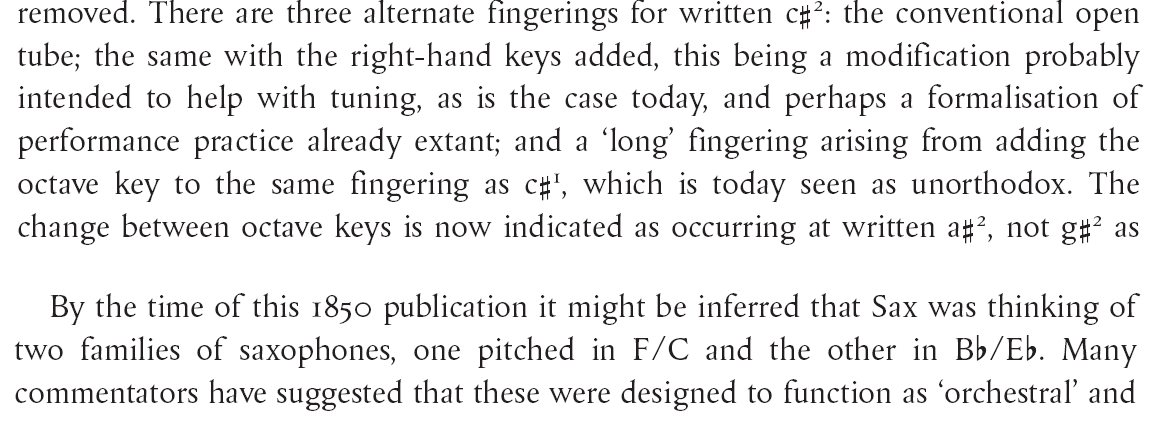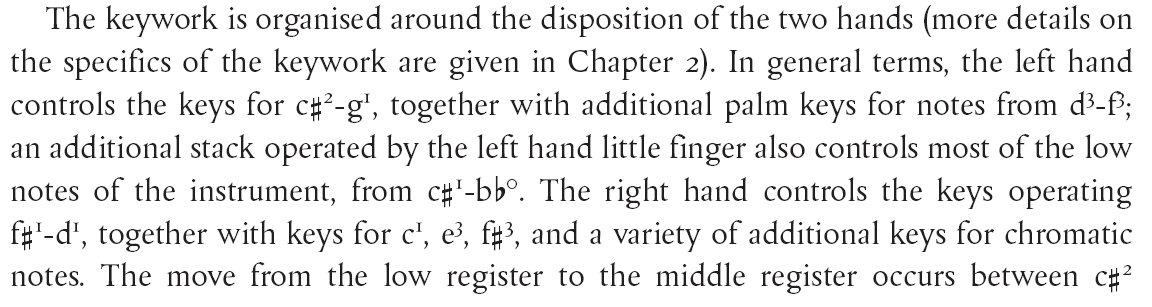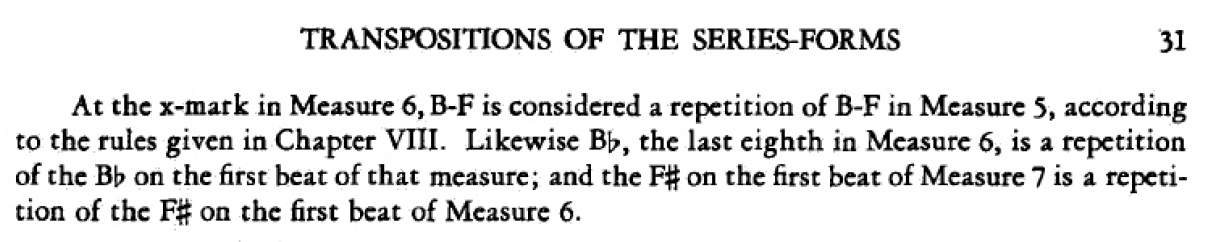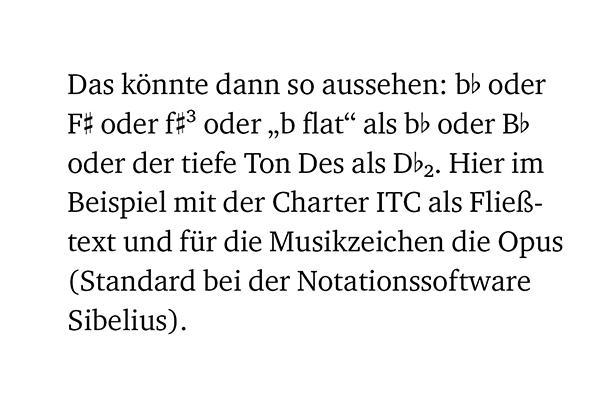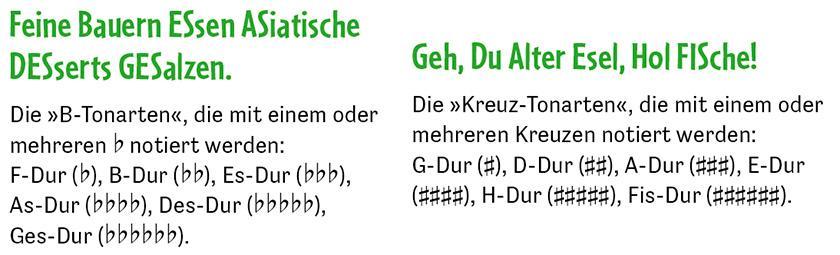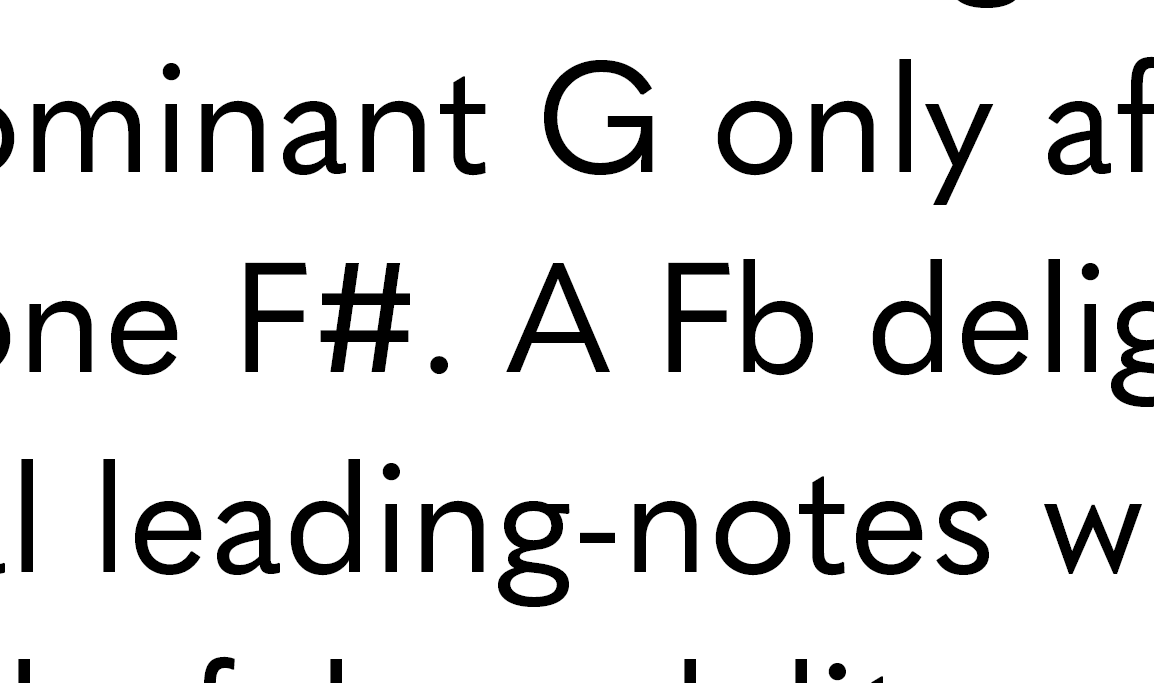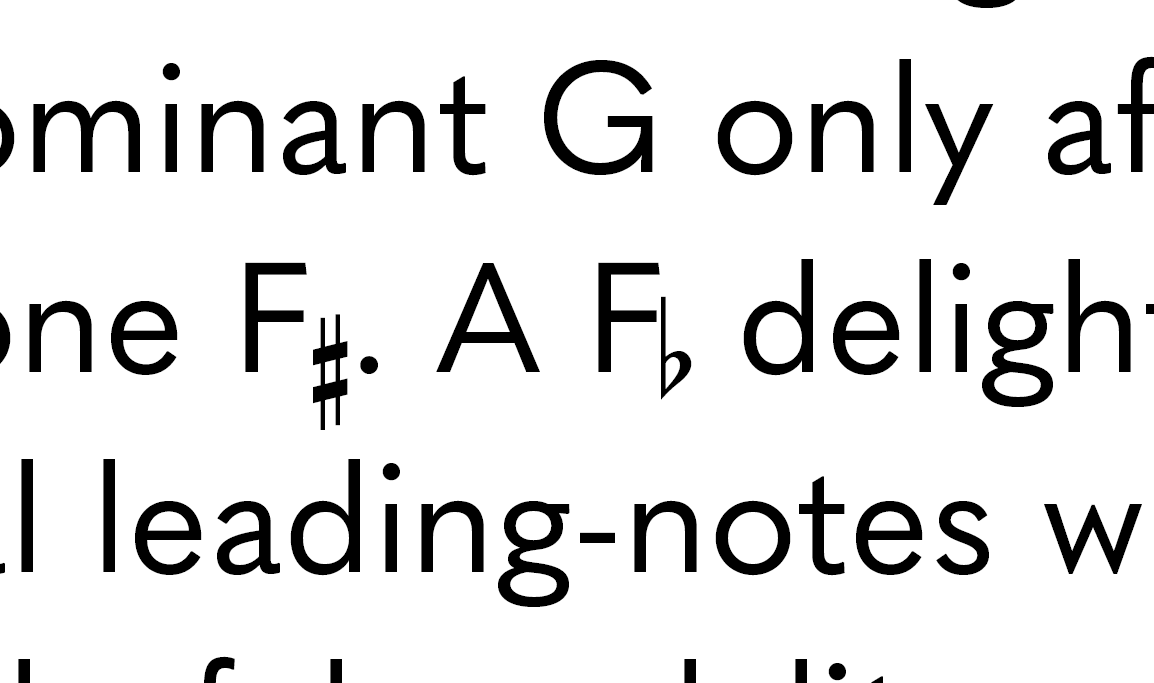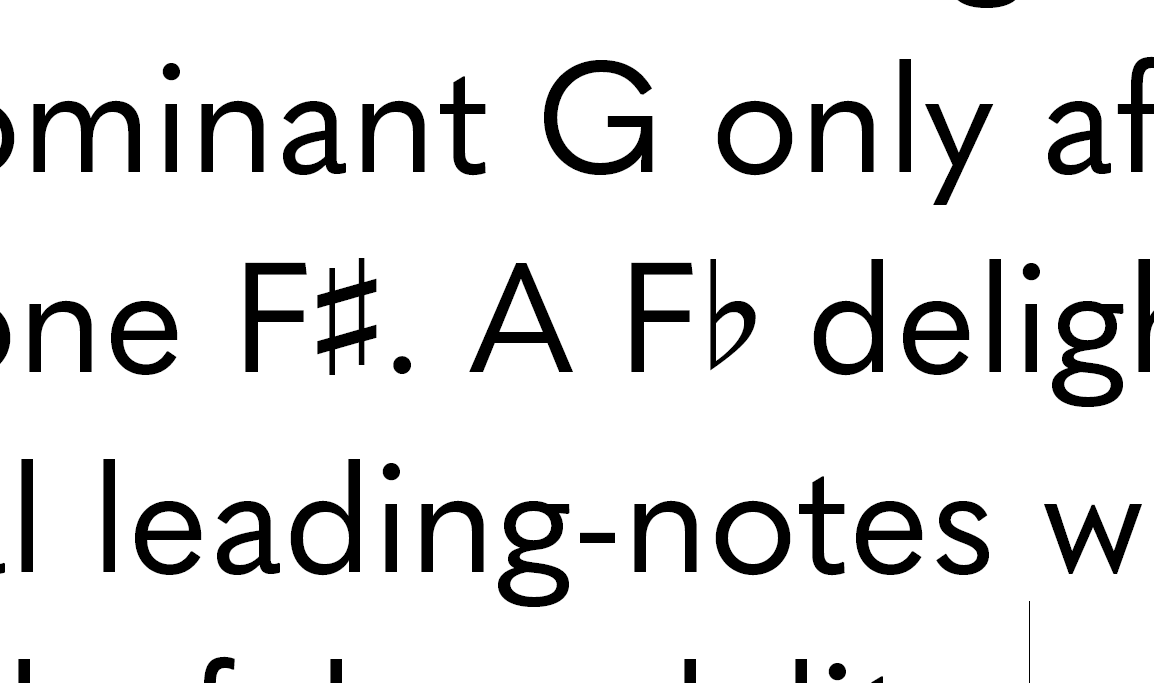
[Mitglied Loth…] Geschrieben 9. Januar Teilen Geschrieben 9. Januar Es ist im englischen Sprachraum durchaus üblich, erhöhte und erniedrigte Noten mit den aus der Notenschrift bekannten Zeichen ♯ und ♭ zu schreiben. Zum Beispiel wird die Note Fis zu F♯, Fes wird zu F♭. Aus der Detailtypografie von De Jong/Forssman weiß ich inzwischen, dass die Verwendung der Raute (#) hier nicht richtig ist. Das kleine »b« in der Brotschrift ist hier nicht deutlich. Das Manuskript sieht aber manchmal so aus: [[Abb. 1]] Tatsächlich enthält unsere Hausschrift die besagten Glyphen gar nicht. Das ♯ konnte ich im Unicode auf Position U+266F (Musical Sharp Sign) und das ♭ auf Position U+266D (Musical Flat Sign) ausfindig machen. Ich bin aber erstaunt, dass nur wenige Fonts die Zeichen beinhalten. Recht klar ist, dass die Sonata Regular von Adobe dabei ist. Das sieht dann so aus: [[Abb. 2]] Das sind richtige Fremdkörper und die Zurichtung ist ja wohl auch nicht für Text gemacht. Ich nehme an, die Sonata ist für den Notensatz gedacht. Nach etwas Recherche habe ich die Arial Unicode MS gefunden. [[Abb. 3]] Ich habe dann jeweils die Größe und den Grundlinienversatz angepasst und an der Mittellänge ausgerichtet. [[Abb. 4]] Link zu diesem Kommentar
[Mitglied Phoi…] Geschrieben 9. Januar Teilen Geschrieben 9. Januar Generell gesagt, sind falsch und richtig relative Größen, typographisch falsch genutztes kann durch die Akzeptanz und Gewohnheit der Zielgruppe zu "richtig" werden oder auch als "richtig" aufgefasst werden, so dass tatsächlich korrekte Anwendungen zu Stolpersteinen werden, die "falsch" wirken -- solange es keine wirklich gute Alternative gibt. Bei Abbildung vier würde ich das Erhöhungszeichen nicht an der Ecken des Querstrichs ausrichten, sondern am oberen Kreuzungspunkt. Ich bin nun kein Experte für irgendwas, aber ich erinnere mich aus dem Schulunterricht, dass die Modifikationen eigentlich vor der Note stehen müssen. Daher finde F# und Fb inkonsequent. #F und bF wären der Notation näher, F# und Fb der sprachlichen Verarbeitung. Ich würde mir da den Konflikt ersparen und einfach Fis und Fes schreiben. Link zu diesem Kommentar
[Mitglied D2C…] Geschrieben 9. Januar Teilen Geschrieben 9. Januar vor 16 Minuten schrieb Phoibos: Generell gesagt, sind falsch und richtig relative Größen, typographisch falsch genutztes kann durch die Akzeptanz und Gewohnheit der Zielgruppe zu "richtig" werden oder auch als "richtig" aufgefasst werden, so dass tatsächlich korrekte Anwendungen zu Stolpersteinen werden, die "falsch" wirken -- solange es keine wirklich gute Alternative gibt. Du meinst so etwas wie »25 x 25cm« statt »25 × 25 cm«? vor 17 Minuten schrieb Phoibos: Ich bin nun kein Experte für irgendwas, aber ich erinnere mich aus dem Schulunterricht, dass die Modifikationen eigentlich vor der Note stehen müssen. Daher finde F# und Fb inkonsequent. #F und bF wären der Notation näher, F# und Fb der sprachlichen Verarbeitung. Ich würde mir da den Konflikt ersparen und einfach Fis und Fes schreiben. Die Bilder legen nahe, dass es um englischen Text geht. »Fis« und »Fes« dürften auf Englisch nicht verstanden werden. 1 Link zu diesem Kommentar
[Mitglied Phoi…] Geschrieben 9. Januar Teilen Geschrieben 9. Januar vor 8 Minuten schrieb D2C: Du meinst so etwas wie »25 x 25cm« statt »25 × 25 cm«? Exakt. Oder drei Punkte statt Dreipunkt. Es gibt so vieles, was aus der Schreibmaschinenzeit sich so ins Zielgruppengedächtnis eingebrannt hat, dass die korrekte Anwendung erstmal zum Stolpern anregt. vor 13 Minuten schrieb D2C: »Fis« und »Fes« dürften auf Englisch nicht verstanden werden. Stimmt, Die Nutzung der Detailtypographie ließ mich an eine Übertragung denken. Die englische Wikipedia kennt übrigens mehrere Unicode-Punkte für das Kreuz: Zitat In Unicode, assigned sharp signs are as follows: U+266F ♯ MUSIC SHARP SIGN (HTML ♯ · ♯) U+1D12A 𝄪 MUSICAL SYMBOL DOUBLE SHARP (HTML 𝄪) U+1D130 𝄰 MUSICAL SYMBOL SHARP UP (HTML 𝄰) U+1D131 𝄱 MUSICAL SYMBOL SHARP DOWN (HTML 𝄱) U+1D132 𝄲 MUSICAL SYMBOL QUARTER TONE SHARP (HTML 𝄲) Link zu diesem Kommentar
[Mitglied Tobi…] Geschrieben 9. Januar Teilen Geschrieben 9. Januar Die gezeigten Beispiele sehen erstmal alle komisch aus. Das liegt evtl. aber auch daran, dass es um Fließtext geht und hier Ausschnitte gezeigt werden. Zum Richtigen Einschätzen, wäre eine ganze Seite mal interessant (zu lesen). Die Gewohnheit des Zielpublikums ist natürlich wichtig, denen kommen diese Zeichen vielleicht nicht so fremd vor wie mir Damit die Zeichen sich mehr einreihen, aber nicht falsch gelesen werden, würde ich mal versuchen # und b zu verwenden, aber das b in dem kursiven Schnitt. Das könnte eine gut lesbarer Kompromiss sein. Dagegen spricht natürlich, dass das ♭ein festes Zeichen ist, ähnlich wie Estimated ℮ oder €. Letzteres zeigt aber, dass konkrete Symbole auch ein Eigenleben bekommen können … Ansonsten finde ich Abb. 4 schon ganz gut. Das # würde ich etwas höher setzen und optisch auf x-Höhe mitteln statt rein rechnerisch nach Hilfslinien. Link zu diesem Kommentar
[Mitglied Henn…] Geschrieben 9. Januar Teilen Geschrieben 9. Januar Spontan hätte ich die Versetzungszeichen klein und hochgestellt gesetzt. Das liegt aber wahrscheinlich daran, dass so Akkordsymbole notiert werden, die ich wesentlich häufiger lese als englischsprachige Literatur. Ich habe mal zwei Beispiele aus Büchern angehängt: Ernst Krenek: Studies in Counterpoint, Schirmer, New York 1940: Stephen Cottrell: The Saxophone, Yale University Press, New Haven and London 2012: 2 Link zu diesem Kommentar
[Mitglied Uwe…] Geschrieben 9. Januar Teilen Geschrieben 9. Januar Hallo, ♯ vor 23 Minuten schrieb HenningH: Spontan hätte ich die Versetzungszeichen klein und hochgestellt gesetzt. Das liegt aber wahrscheinlich daran, dass so Akkordsymbole notiert werden, die ich wesentlich häufiger lese als englischsprachige Literatur. ...[...]... Stephen Cottrell: The Saxophone, Yale University Press, New Haven and London 2012: Der letzte Absatz ist inkonsequent? Bei B♭/E♭ ist das ♭ nicht runtergesetzt, das ♯ ist es jedoch. Oder wird da ein Unterschied zwischen Note und Tonart gemacht? Ich bin übrigens auch die hochgesetzten ♭ und ♯ von den Akkordsymbolen gewohnt. MfG Link zu diesem Kommentar
[Mitglied Thom…] Geschrieben 9. Januar Teilen Geschrieben 9. Januar Hier ein Beispiel aus der eigenen Mache. Die Musikzeichen sind aus der Textschrift (Kaius) und nicht aus einer speziellen Notenschrift gesetzt. Sie fügen sich daher gut ein, entbehren aber des für Notenzeichen typischen Strichkontrasts. 1 Link zu diesem Kommentar
[Mitglied Tobi…] Geschrieben 9. Januar Teilen Geschrieben 9. Januar vor 4 Minuten schrieb Thomas Kunz: entbehren aber des für Notenzeichen typischen Strichkontrasts. Das ♭ist aber als solches gut erkennbar, wird nicht sofort mit dem b verwechselt und fällt nicht aus der Reihe – finde ich für Fließtext gut 👍🏻 1 Link zu diesem Kommentar
[Mitglied Henn…] Geschrieben 9. Januar Teilen Geschrieben 9. Januar Noch ein Beispiel aus dem zweiten Buch: Link zu diesem Kommentar
Ralf Herrmann Geschrieben 9. Januar Teilen Geschrieben 9. Januar vor 7 Stunden schrieb Lothar B.: Ich bin aber erstaunt, dass nur wenige Fonts die Zeichen beinhalten. Als Schriftgestalter ist man mit einem Unicode-Vorrat von über 100.000 Zeichen konfrontiert. Da muss man sich klare Grenzen stecken, zum Beispiel Standardzeichensätze (wie Latin 1) oder Sprachräume, die dann auch gern nochmal nach Nähe eingegrenzt werden. Damit deckt man dann z.B. Europa mit lateinischer Schrift komplett ab, aber womöglich nicht das »ferne« Vietnamesisch, denn das weltweite Lateinisch wäre schon wieder ein Fass ohne Boden. Für alles, was darüber hinaus geht, gilt das natürlich genauso. Für normale kommerzielle Schriften zur allgemeinen Anwendung wäre es reine Willkür, jetzt zum Beispiel Musikzeichen einzubauen und es gäbe buchstäblich tausende andere Zeichen, die einzelne Anwender genauso dringend bräuchten. Daher wird sowas nicht abgedeckt und die Anwender greifen dann entweder Themen-Spezial-Fonts oder aber zu Fonts, wo Zeichenvorrat vor gestalterischer Eigenheit und Vielseitigkeit (z.B. in Bezug auf Schnitte) geht. Darunter fällt dann sowas wie Arial Unicode MS. 1 Link zu diesem Kommentar
[Mitglied Norb…] Geschrieben 9. Januar Teilen Geschrieben 9. Januar vor 56 Minuten schrieb Ralf Herrmann: Arial Unicode MS. Damit habe ich mich beispielsweise hier beholfen … nicht optimal, aber akzeptabel … 2 Link zu diesem Kommentar
[Mitglied Tobi…] Geschrieben 13. Januar Teilen Geschrieben 13. Januar Thomas, sorry. Das hatte ich nicht gesehen. Dann sind wir uns ja erst recht einig Dieter, ich wusste, dass sowas kommt. Ja es gibt auch Kleinbuchstabe = Moll. Das würde ich aber nicht nutzen, spätestens wenn ich im Unterricht nen kleines und nen großes C von Hand schreibe rafft keiner mehr, ob Dur oder Moll. Daher lieber C und Cm (oder notfalls C- wie die Angelsachsen das gerne mal machen) 1 Link zu diesem Kommentar